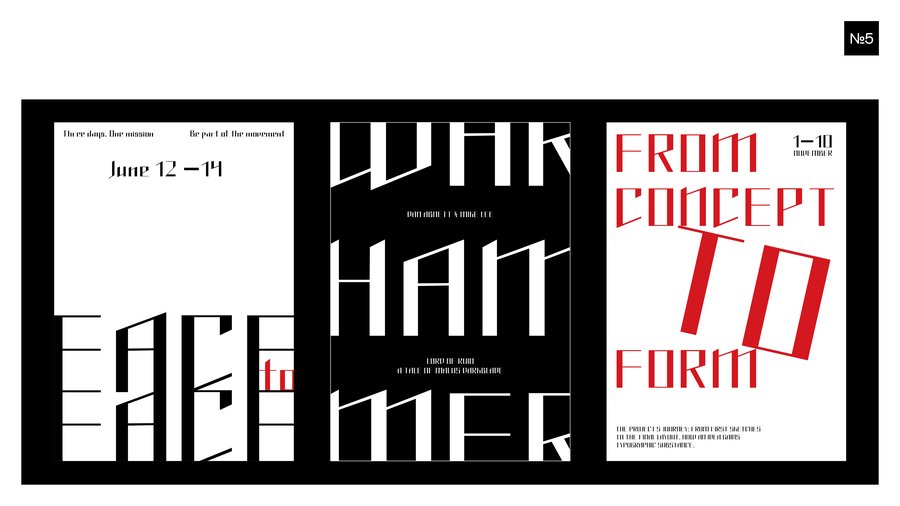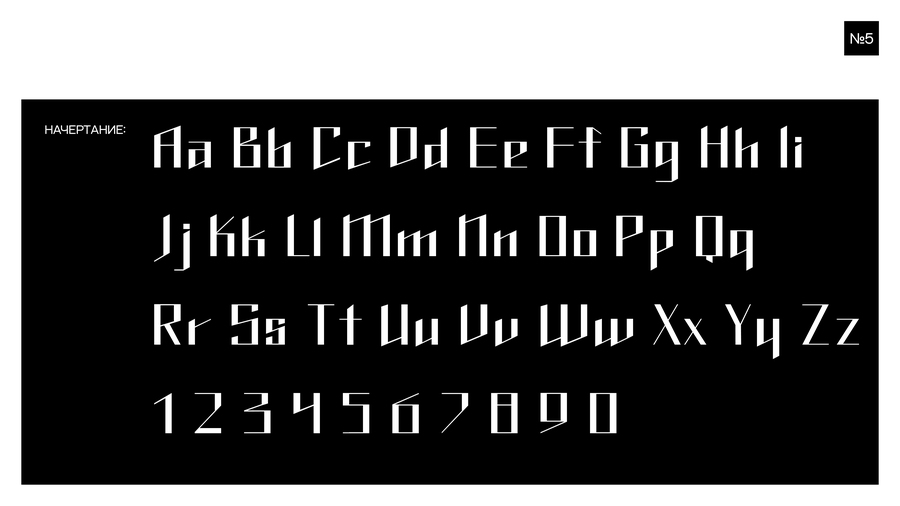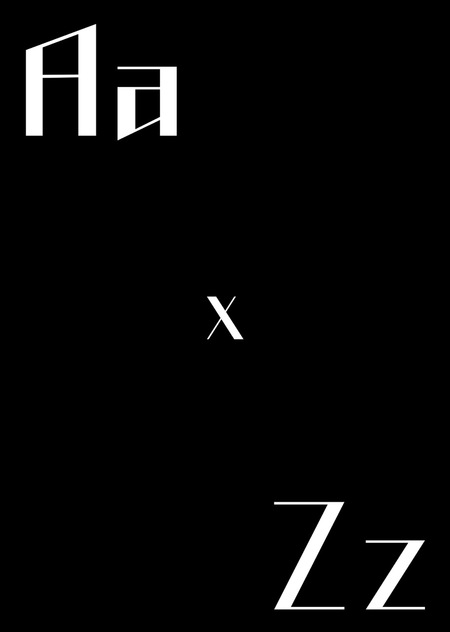
Шрифт Pivovarova — авторский контрастный гротеск. Острота контуров и резкие срезы придают ему динамичный, энергичный характер, а баланс строгой структуры и творческой свободы сохраняет читаемость. В проекте проработаны основные начертания, лигатуры и специальные символы — шрифт подходит для заголовков и акцентных надписей. Он задуман как часть персонального визуального языка и может усиливать айдентику проекта.